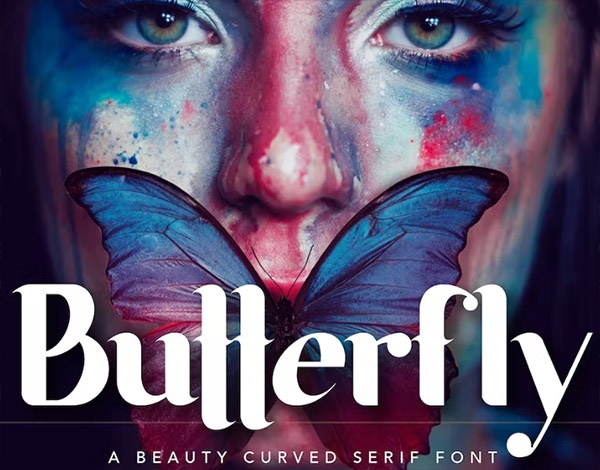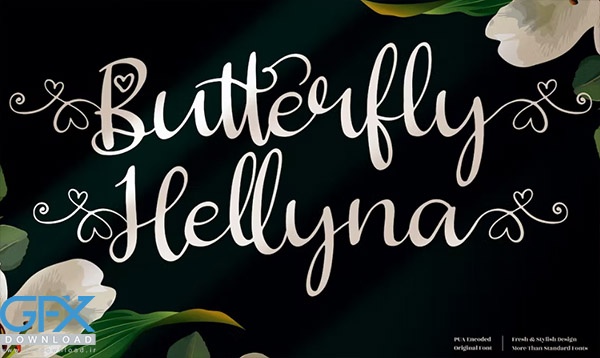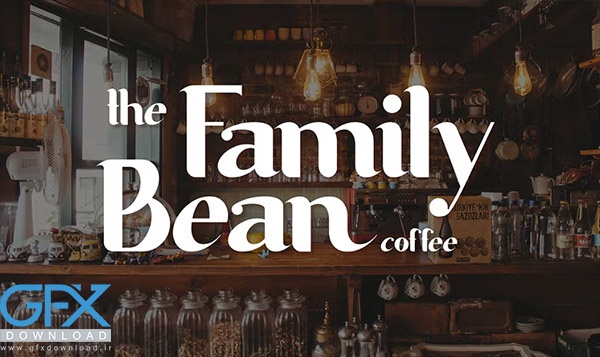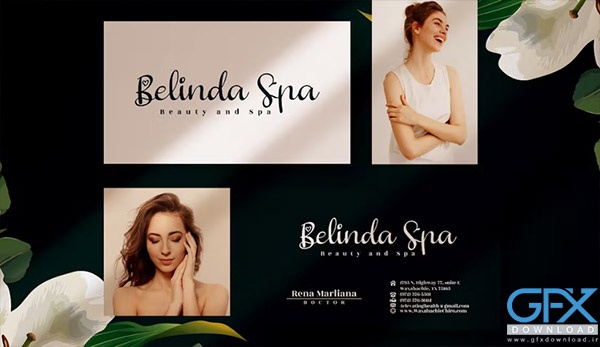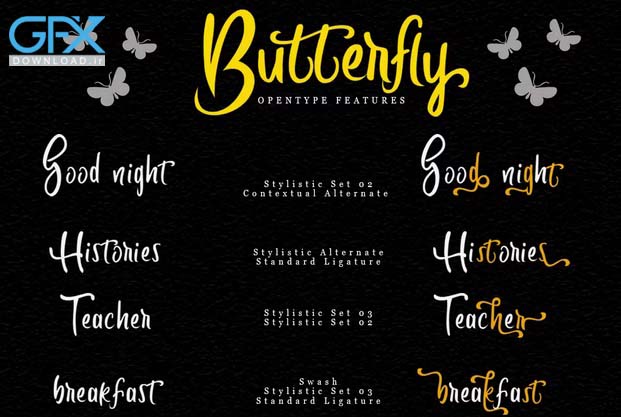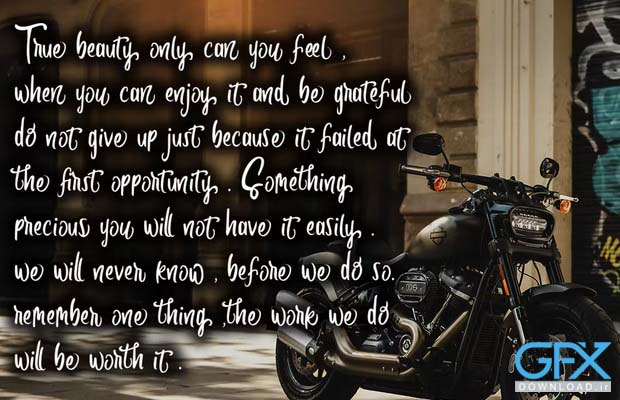
دانلود 2 فونت انگلیسی پروانه ای🦋جدید
فونت های انگلیسی پروانه ای زیبا
دانلود فونت های انگلیسی پروانه ای زیبا
این یکی از فونت های انگلیسی زیبا است که برای تکمیل محصولات خلاقانه دیجیتال و چاپی شما مناسب است. این فونت برای پوسترها، پست های رسانه های اجتماعی، برندسازی، پروژه های شخصی و غیره مناسب است. دانلود فونت انگلیسی پروانه ای یک فونت زیبای معاصر با لیگاتورهای زیبا و جایگزین است. این یک فونت نمایشی است که برای پروژه های برندسازی، لوگو، طرح های عروسی، پست های رسانه های اجتماعی، تبلیغات، متن نقل قول شده، کافی شاپ، بسته بندی محصول، طرح های محصول، برچسب، عکاسی، واترمارک، دعوت نامه، لوازم التحریر و هر پروژه ای که می سازد عالی است.
🦋 نام فونت انگلیسی1: Butterfly Beauty - Butterfly Hellyna
🦋 نام فونت2: Butterfly Modern Script
🦋 حروف بزرگ و کوچک
🦋 حروف کوچک جایگزین
🦋 شماره گذاری و نقطه گذاری
🦋 لیگاتورها